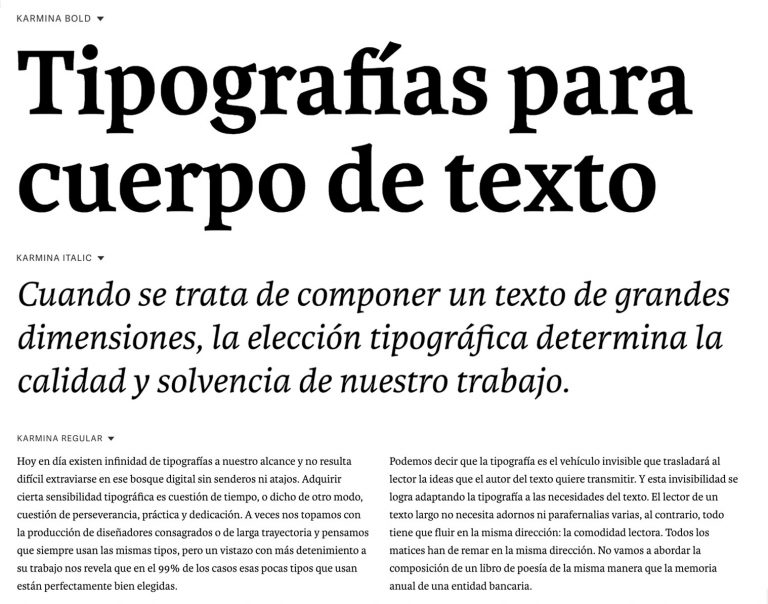
Karmina vía www.type-together.com
Elegir la tipografía adecuada es uno de los asuntos centrales en cualquier trabajo de diseño gráfico. Pero cuando se trata de componer un texto de grandes dimensiones —una novela, una tesis o un informe técnico— entonces la importancia de nuestra elección es absoluta, pues solo vamos a trabajar con tipografía y ésta, por lo tanto, determinará la calidad y solvencia de nuestro trabajo.
Veamos a continuación algunos puntos importantes que debemos tener en cuenta a la hora de abordar trabajos de diseño con grandes cantidades de texto y que nos pueden ayudar a elegir la tipografía adecuada para cada ocasión.
Necesidades del texto
Los diseñadores debemos hacernos una serie de preguntas para ser capaces de elegir la tipografía que presente las características idóneas para cada proyecto: ¿necesito una tipo con suficiente variedad de pesos?, ¿voy a utilizar versalitas?, ¿números y fracciones, ligaduras y negritas?, ¿el proyecto va adaptado a distintos idiomas?, etc. Las respuestas a estas preguntas acotarán la búsqueda por el “bosque digital tipográfico” sin senderos ni atajos y por el que no resulta difícil extraviarse.
Karmina en uso: Cómo crear tipografías. Del boceto a la pantalla. Ed. Tipo-e vía fontsinuse.com
Sensibilidad tipográfica
El diseño editorial requiere de precisión y sensibilidad a partes iguales; es quizá la rama del diseño gráfico en que más necesario resulta aunar los conocimientos técnicos y las decisiones estéticas. Pero no os preocupéis, que adquirir cierta sensibilidad tipográfica es solo cuestión de tiempo.
A veces nos topamos con la producción de diseñadores consagrados o de larga trayectoria y pensamos que siempre usan las mismas tipos, pero un vistazo con más detenimiento a su trabajo nos revela que en el 99% de los casos esas pocas tipos que usan están perfectamente bien elegidas. No se es mejor pintor por usar una paleta muy amplia, sino por poseer una gama propia y reconocible, perfectamente adaptada a lo que se quiere expresar.
No distraigas al lector
Podemos decir que la tipografía es el vehículo invisible que trasladará al lector la ideas que el autor del texto quiere transmitir. Y esta invisibilidad se logra adaptando la tipografía a las necesidades del texto. El lector de un texto largo no necesita adornos ni parafernalias varias, al contrario, todo tiene que fluir en la misma dirección: la comodidad lectora. No vamos a abordar la composición de un libro de poesía de la misma manera que la memoria anual de una entidad bancaria.
Libros digitales & libros «analógicos»
Actualmente, cuando hablamos de cuerpo de texto, nos estamos refiriendo a dos medios diferentes: el libro impreso por un lado y el medio digital por otro. Los avances técnicos del segundo han ido eliminando diferencias entre ambos medios y, por ejemplo, al inicio de la era digital, era habitual usar tipografías de palo seco para digital debido a la baja resolución de las pantallas. Pero en las pantallas de hoy en día, en los dispositivos electrónicos de lectura, con una resolución tan alta, podemos usar tranquilamente, al igual que en los libros físicos, tipografías con serif, porque vamos a obtener una comodidad lectora totalmente aceptable.
Pensum en uso vía www.typemates.com
Invitación a la lectura
Un detalle muy relevante que no se nos debe escapar nunca es que la tipografía que elijamos puede aumentar o disminuir el número de páginas del trabajo que vayamos a componer, lo que puede hacer variar, por ejemplo, la factura de la imprenta. Esto no quiere decir ni mucho menos que siempre tengamos que escoger la fuente que menos espacio nos ocupe. El diseño de cada pieza deberá respetar la extensión adecuada y observar siempre la legibilidad y lecturabilidad del texto. Estos dos conceptos expresan ideas cercanas que hay que tener en cuenta. El segundo está en cursiva porque el diccionario de la Academia no lo recoge, pero tipográficamente hablando es muy útil. Pongamos un ejemplo: la Helvetica es una tipografía altamente legible, ¿verdad?, se lee con mucha facilidad, pero si componemos Guerra y paz con la Helvetica Ultra Compressed a un tamaño menor de 8 puntos el resultado podrá ser legible, pero no será para nada lecturable, es decir, no invitará a la lectura. Resumiendo: lecturabilidad es igual a sentido común.
Tamaño e interlineado
El rendimiento de una tipo es una cuestión que atañe también al tamaño ya que dependiendo de la “altura de x” que tenga cada tipo así se será la cantidad de texto que podamos encajar en la página. Por lo general suele encontrarse entre 9 o 9,5 y 10,5 u 11pt. Pero no hay un número fijo ni una receta secreta para elegir el tamaño, siempre es aconsejable imprimir una página y como dice José Ramón Penela (Unos tipos duros) “dejar que el ojo tipográfico decida.”
Respecto al interlineado, por regla general, supone el 120% del cuerpo. Por ejemplo, a un cuerpo de 10 puntos le corresponderá un interlineado de 12 puntos pero a veces esta relación cuerpo-interlineado dependerá de varios factores como, por ejemplo, el tamaño del ojo medio de la letra, esto es, el tamaño de “altura x” con respecto a sus astas descendentes y ascendentes. Cuando el ojo medio de la letra es pequeño aumenta el espacio blanco entre líneas y facilita la lectura de lo contrario puede dificultar la velocidad de la misma.
Hasta aquí algunos puntos importantes que debemos tener en cuenta a la hora de abordar trabajos de diseño con grandes cantidades de texto. El tema es amplio y da para extenderse. De cada punto y cada concepto podríamos hacer un spin-off y no dudamos en hacerlo más adelante pero no queremos terminar este artículo sin echaros un cable tipográfico para ese momentazo que es elegir una tipo para cuerpo de texto. A continuación, demos un paseo por siete tipos para cuerpo de texto para un acabado de diez.
Inka, de Carnoky Type
Inka es la benjamina de esta selección tipográfica y nuestra apuesta personal. La consideramos perfecta para libros, periódicos o revistas gracias al amplio repertorio de estilos y conjunto de glifos. Una gran familia versátil y bien avenida que destaca en tamaños grandes y se hace «invisible» en cuerpo de texto. Sin duda, le auguramos grandes éxitos en diseño editorial.
Tipografía Inka de Samuel Carnoky vía www.behance.net